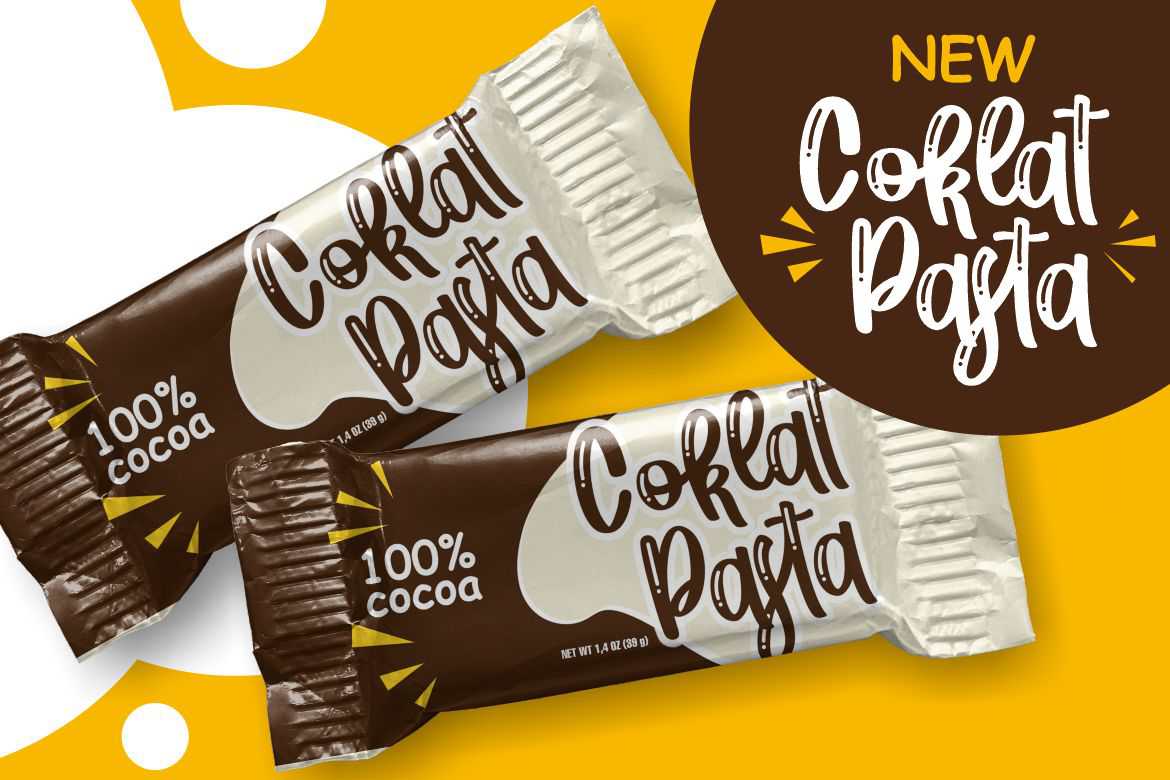
lafiesta是一款甜美而独特的手工风格,是阿曼设计项目的完美之选!白色轮廓不包括在内,但您可以使用轮廓效果良好的Coreld Draw或在Photoshop中隐藏。它对于剪影和轮廓手工艺师来说是非常平滑的,使其成为乙烯项目的最佳选择!lafiesta是一款甜美而独特的手工风格,是阿曼设计项目的完美之选!白色轮廓不包括在内,但您可以使用轮廓效果良好的Coreld Draw或在Photoshop中隐藏。它对于剪影和轮廓手工艺师来说是非常平滑的,使其成为乙烯项目的最佳选择!